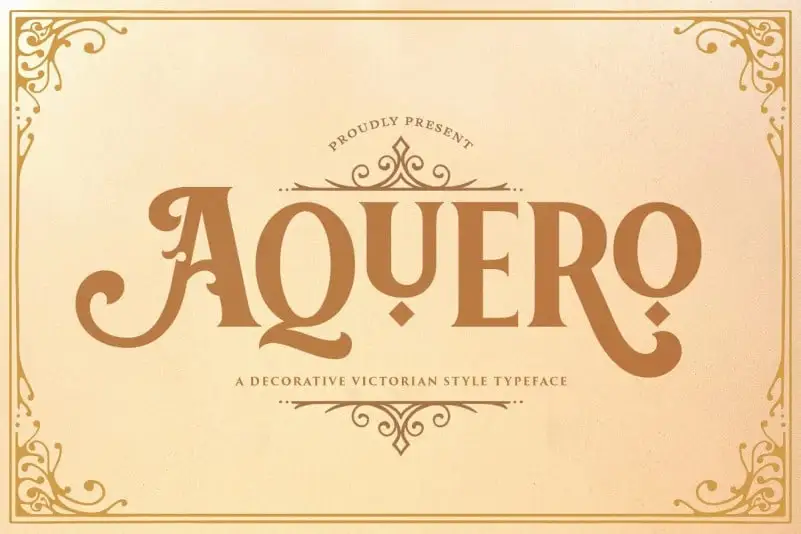
Aquero Display Font – Fonte Grátis
Aquero Display Font
A Aquero Display Font é uma elegante fonte serif que traz a sensação do passado nostálgico em suas linhas modernas e sofisticadas. Feita pelo font designer StringLabs, essa fonte se destaca com detalhes meticulosos e um toque suave de nostalgia, tornando-a perfeita para design contemporâneo ou clássico. Inspirada nas designs de tatuagem vintage, Aquero oferece uma aparência impactante que chama a atenção sem perder o charme românico da fonte serif. Perfeito tanto para um design moderno quanto clássico, Aquero exibe sua forma romântica e agressiva de maneira impressionante. Suas linhas delicadas são perfeitamente complementadas por seus detalhes cuidadosos que proporcionam uma aparência única e impecável. Combinada em designs variados, a fonte se destaca como uma opção excepcional para aqueles buscando um toque vintage moderno sem perder o charme de uma tipografia serif clássica. Neste contexto, a Aquero Display Font é uma escolha perfeita tanto para designers gráficos quanto para quem busca um elemento único e memorável em seus projetos. Seja em um design minimalista ou elaborado, a fonte contribuirá com sua beleza e originalidade, garantindo um visual respeitável que chama atenção de maneira harmoniosa.